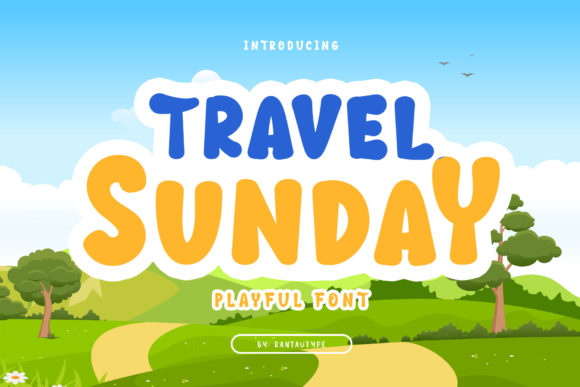
Путешествия воскресенье милый и веселый шрифт дисплея.
Он воплощает в себе игривость и подлинность и является идеальным выбором для любого детского мероприятия или школьного проекта.
Добавьте этот лохматый шрифт к вашим дизайнам и заметьте, как он заставляет их оживать!